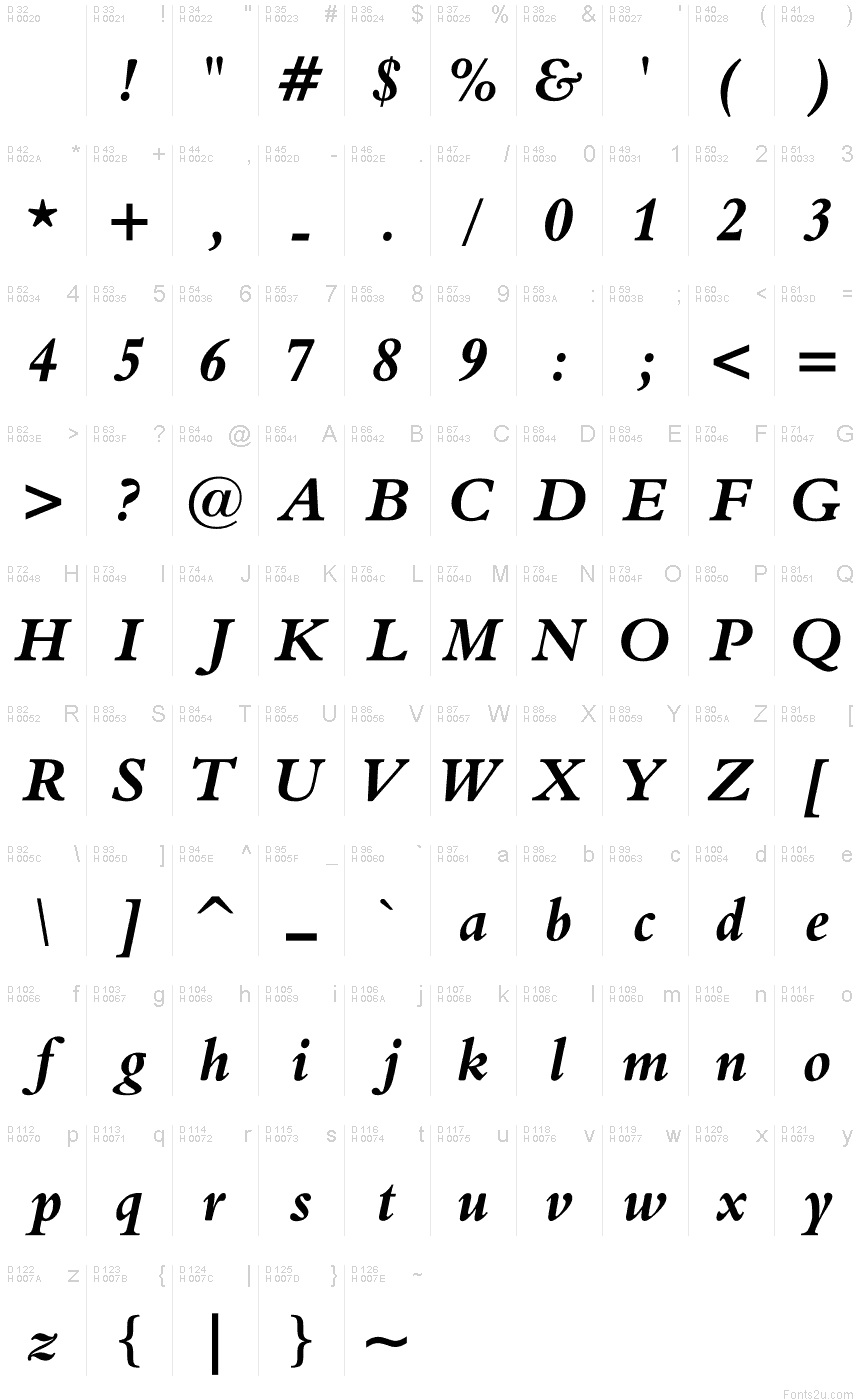
UKIJ Chiwer Kesme, proposée par la Uyghur Computer Science Association, est une police serif italique gratuite au style formel et lettré. Les lettres se penchent avec la fluidité d'une écriture calligraphique, mariant un contraste marqué à de larges empattements incurvés ; le J à longue descendante apporte à l'ensemble un rythme résolument littéraire.
Elle convient aux projets en quête d'une autorité classique sans rigidité : têtes de chapitres, affiches culturelles, couvertures de livres, graphisme muséal ou cartons de titres. En tant que police gratuite, elle excelle également pour les monogrammes et les textes courts, où ses capitales élancées et ses jointures nettes confèrent une présence solennelle, même sur un petit nombre de caractères.